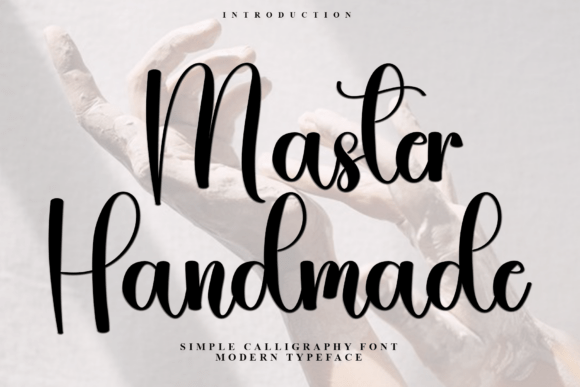
Master Handmade
Master Handmade์™€ ๊ฐ™์€ ๊ณ ํ’ˆ์งˆ ์ž์‚ฐ์„ ์ฐพ๊ณ  ์žˆ๋‹ค๋ฉด ์ด ํ”„๋ฆฌ๋ฏธ์—„ ํŒจํ‚ค์ง€๋Š” ์ฐฝ์˜์ ์ธ ํ”„๋กœ์ ํŠธ๋ฅผ ์œ„ํ•œ ํ™˜์ƒ์ ์ธ ์„ ํƒ์ž…๋‹ˆ๋‹ค.
POD(์ฃผ๋ฌธํ˜• ์ธ์‡„) ์ œํ’ˆ, ๊ฒฐํ˜ผ์‹ ์ดˆ๋Œ€์žฅ ๋˜๋Š” ์†Œ์…œ ๋ฏธ๋””์–ด ๊ทธ๋ž˜ํ”ฝ์„ ๋งŒ๋“ค ๋•Œ Master Handmade๋Š” ์ด์ƒ์ ์ธ ์„ ํƒ์ž…๋‹ˆ๋‹ค.